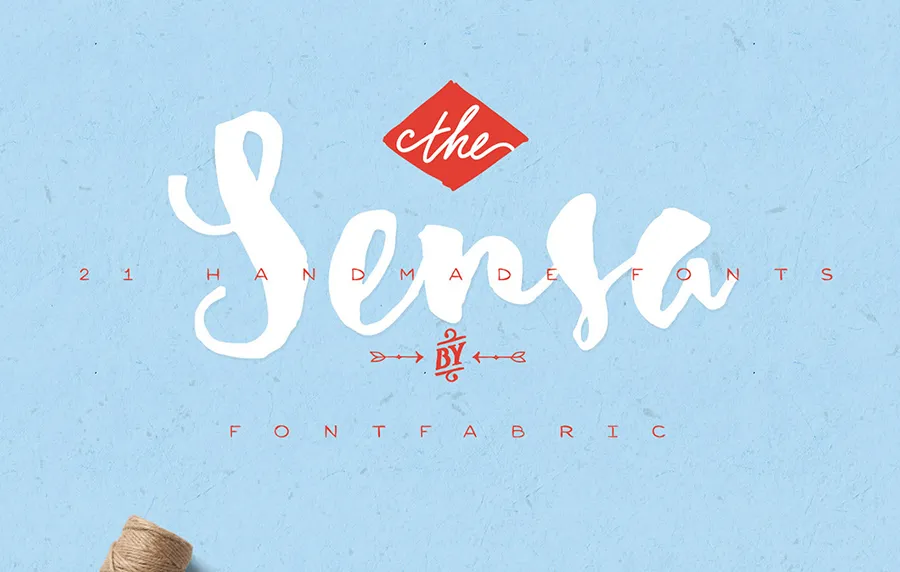
Sensa Font
Sensa é uma família de fóntes artesanal composta por 21 fóntes. Ela se divide em seis subfamilias que contribuem para seu poder visual extenso – Sensa Brush, Sensa Pen, Sensa Wild, Sensa Sans, Sensa Serif e Sensa Goodies. Esta família de letras oferece uma grande variedade de opções, sendo perfeitamente adaptada para diferentes projetos gráficos. Se você está procurando por uma fonte versátil e criativa para seus trabalhos, Sensa pode ser a solução certa. Fornecemos gratuitamente um demo incluindo as fóntes Sensa Brush e Sensa Sans. Teste hoje mesmo Sensa Font!